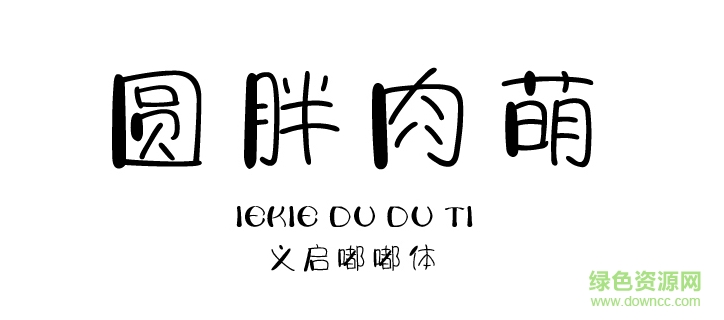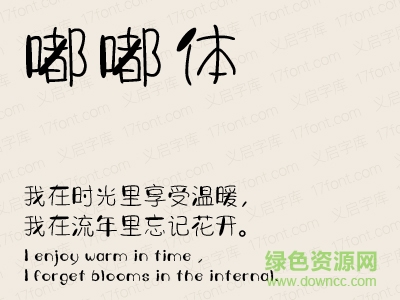
義啟嘟嘟體字體是一款非??蓯鄣?a href="http://m.lz0519.com/k/yiqiziti/" target="_blank">義啟字體,這款字體字形偏胖,看起來非常舒適,比較適用于卡通形象設(shè)計(jì)領(lǐng)域,喜歡的朋友歡迎來綠色資源網(wǎng)下載使用!
“我不是胖嘟嘟,只是我的肉很多”,這是曹格的女兒Grace說的一段很經(jīng)典的話,這款嘟嘟體設(shè)計(jì)就是來源于這個(gè)胖嘟嘟并且很可愛的小女孩,但是這款字體卻不顯胖,反而顯得特別可愛,所以我們叫她“嘟嘟體”。這款字體不像黑體那樣筆畫一樣,顯得更加輕松愜意,部分地方加粗,有點(diǎn)胖嘟嘟的感覺,卻一點(diǎn)不顯臃腫,反而覺得特別可愛。